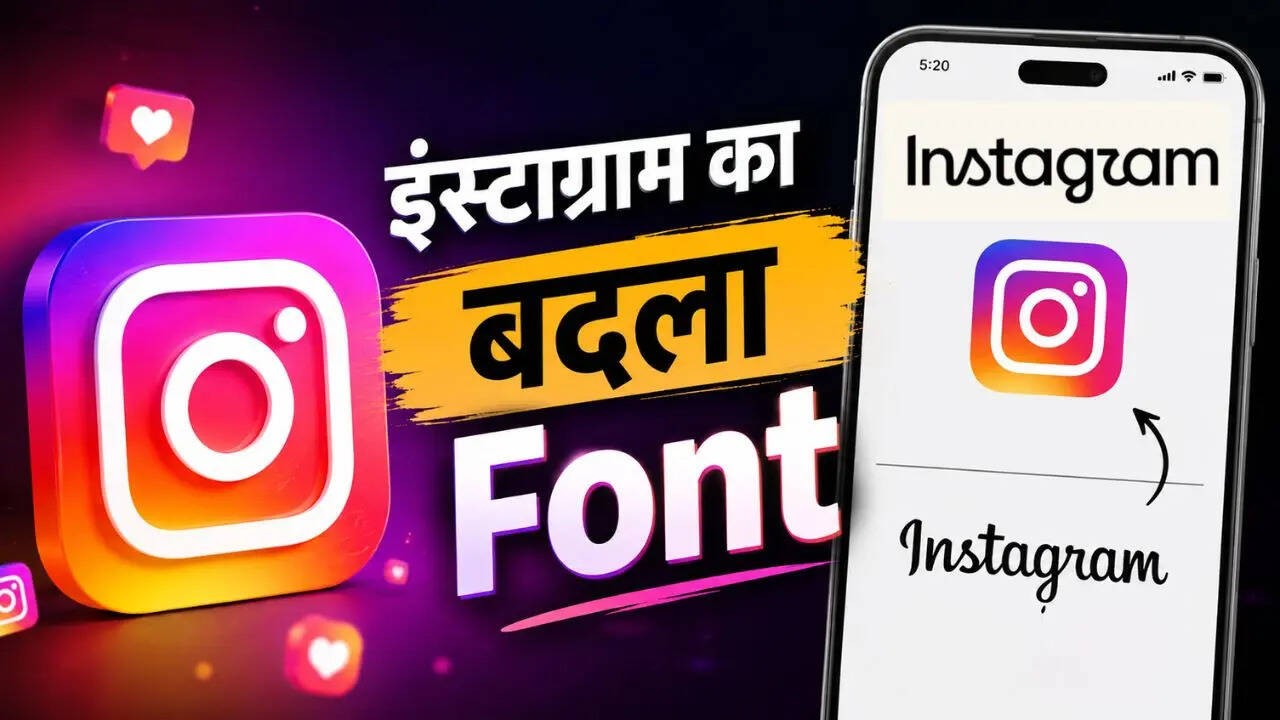
अगर आपने हाल ही में अपने फोन में इंस्टाग्राम ऐप(Instagram) ओपन किया होगा, तो ऐप के सबसे ऊपरी हिस्से पर नजर पड़ते ही आपको कुछ नयापन महसूस हुआ होगा। मेटा (Meta) के स्वामित्व वाले लोकप्रिय सोशल मीडिया प्लेटफॉर्म इंस्टाग्राम ने लगभग एक दशक (10 साल) के बाद अपने विजुअल लुक और 'वर्डमार्क' (Wordmark) लोगो को रिफ्रेश कर दिया है। कंपनी के हेड एडम मोसेरी (Adam Mosseri) ने इस नए वर्डमार्क डिजाइन का आधिकारिक तौर पर ऐलान किया। यह बदलाव Android और iOS दोनों ही प्लेटफॉर्म के यूज़र्स के लिए धीरे-धीरे रोलआउट किया जा रहा है।
ऐप आइकॉन में नहीं हुआ बदलाव
सबसे पहले यह समझना जरूरी है कि इंस्टाग्राम ने अपने पूरे ऐप आइकॉन (App Icon) को नहीं बदला है। यानी आपके फोन की होम स्क्रीन पर दिखने वाला गुलाबी, बैंगनी और नारंगी शेड वाला कैमरा आइकॉन बिल्कुल पहले जैसा ही है। कंपनी ने बदलाव केवल उस लिखे हुए 'Instagram' नाम में किया है, जो ऐप के अंदर टॉप हेडर (Header) पर दिखाई देता है।
क्या हुआ बदलाव?
अगर बात करें कि पुराने और नए लुक में क्या अंतर आया है, तो पिछले 10 सालों से इंस्टाग्राम का नाम एक खास कर्सिव (हाथ से लिखे हुए) फ्लोइंग फॉन्ट स्टाइल में दिखता था। नए वर्डमार्क में इस फॉन्ट को थोड़ा अधिक क्लीन, बोल्ड और मॉडर्न रूप दिया गया है। इसमें अक्षरों विशेषकर 's', 'r' और 'g' के घुमाव और डिजाइन में सूक्ष्म बदलाव किए गए हैं। कंपनी का कहना है कि यह नया टाइपफेस डिजिटल स्क्रीन पर पढ़ने में ज्यादा आसान (Readable) है और आधुनिक दौर के हिसाब से डिजाइन किया गया है।
हालांकि, जैसे ही यह नया लुक यूज़र्स की स्क्रीन पर आया, सोशल मीडिया पर इसको लेकर मिली-जुली प्रतिक्रियाएं और मीम्स की बाढ़ आ गई। कई यूज़र्स को यह नया और साफ-सुथरा लुक काफी पसंद आया, वहीं दूसरी तरफ कई लोगों ने इंस्टाग्राम को ट्रोल करना शुरू कर दिया। कुछ लोगों का कहना है कि नए अक्षरों की बनावट के कारण यह पहली नजर में 'Instagram' के बजाय 'Instagzam' जैसा दिखता है! वहीं कई यूज़र्स का मानना है कि पुराने कर्सिव फॉन्ट में जो 'विंटेज चार्म' था, वह इस नए लुक में थोड़ा कम हो गया है।
10 साल पहले बदला था आइकॉन
ब्रांडिंग एक्सपर्ट्स का मानना है कि किसी भी बड़े प्लेटफॉर्म के विजुअल एलिमेंट्स में बदलाव आने पर शुरुआत में ऐसा रिएक्शन आना स्वाभाविक है। इंस्टाग्राम ने आखिरी बार 2016 में अपने आइकॉन और वर्डमार्क को एक साथ बदला था, जिसके बाद से यूज़र्स की आंखों को वही पुराना कर्सिव नाम देखने की आदत हो गई थी। एडम मोसेरी के मुताबिक, कंपनी अपनी पुरानी पहचान और सिंप्लिसिटी को बनाए रखते हुए ऐप के लुक को आधुनिक स्क्रीन्स के मुताबिक नयापन देना चाहती थी। यदि आपके ऐप में अभी तक नया लोगो नहीं दिख रहा है, तो गूगल प्ले स्टोर या एप्पल ऐप स्टोर से ऐप को अपडेट करते ही यह नया लुक दिखाई देने लगेगा।